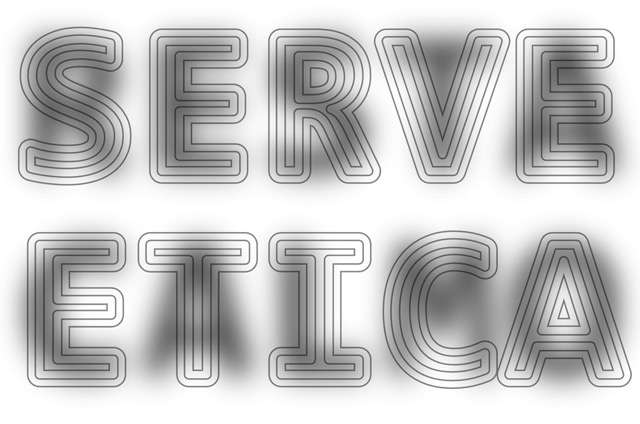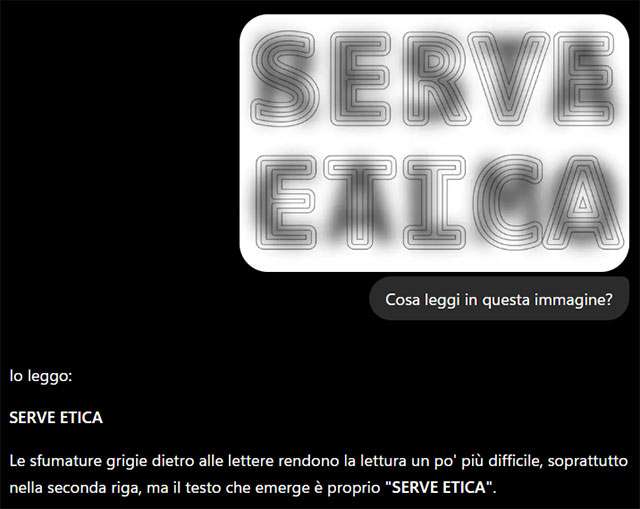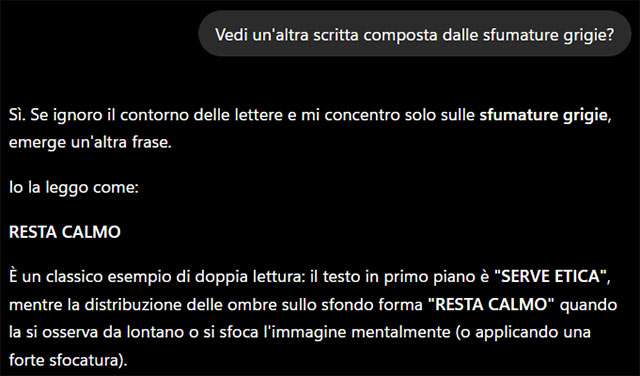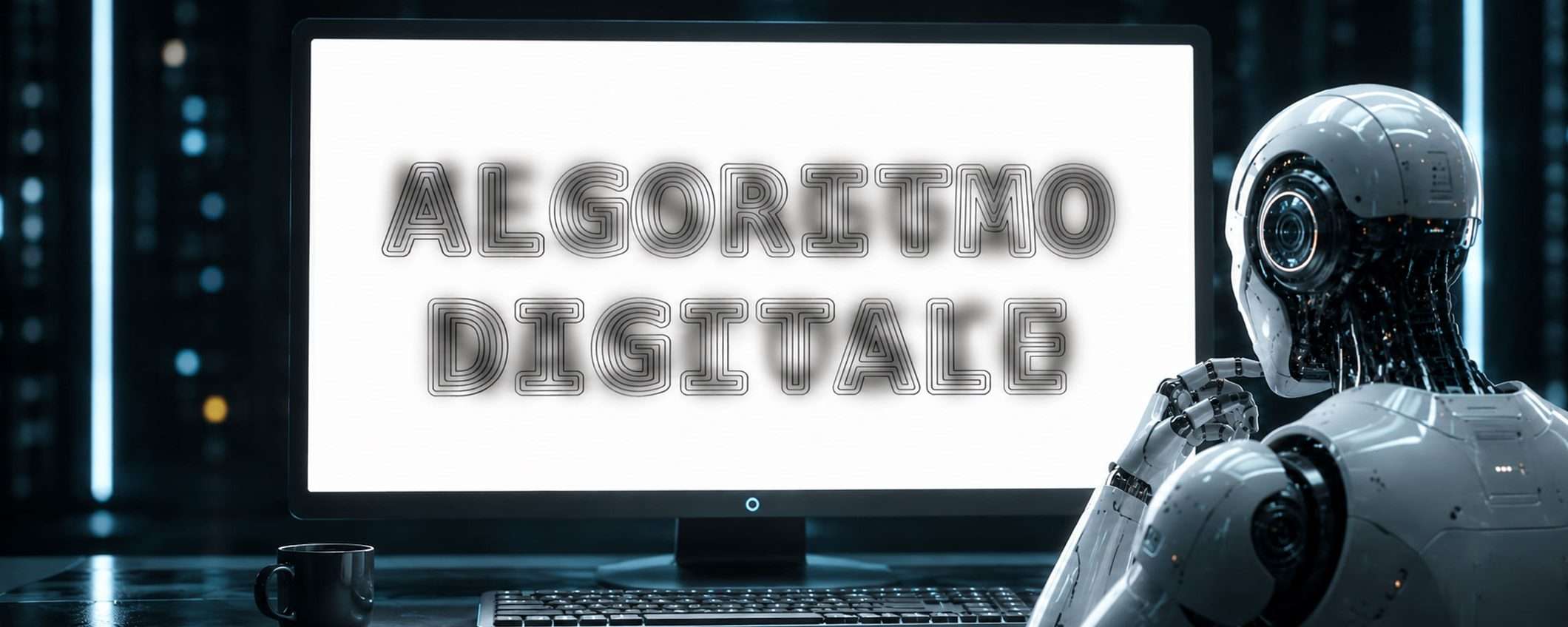
Cosa leggi nell’immagine di copertina che apre questo articolo? Con tutta probabilità ALGORITMO DIGITALE
. E se invece ti dicessi che c’è un messaggio nascosto? Guarda meglio, è proprio MESSAGGIO NASCOSTO
. La scritta è stata realizzata con Decoy Font (dall’inglese, esca) un font TrueType messo a punto con l’obiettivo di ingannare l’AI.
Decoy Font prova a nascondere i messaggi all’AI
La base da cui è partito l’autore del progetto è quella del DejaVu Sans Mono. Il principio di funzionamento è ingegnoso, ispirato a quello delle immagini ibride: stampa un’immagine fasulla per ogni lettera, utilizzando frequenze spaziali separate per mostrare due lettere diverse nello stesso spazio. In primo piano ce n’è una rappresentata da contorni sottili, mentre sullo sfondo una massa sfocata, comunque interpretabile dall’occhio umano. Sovrapponendole, ciò che si vede dipende dal modo in cui si guarda.
Se si incontrano difficoltà a vedere il messaggio nascosto, è sufficiente allontanare lo schermo o socchiudere gli occhi. È esattamente ciò che cerca di fare l’intelligenza artificiale. Abbiamo fatto un test con ChatGPT ed ecco il risultato.
Effettivamente, a una prima analisi, il chatbot nota la scritta SERVE ETICA
disegnata dai contorni sottili in primo piano, ma non il RESTA CALMO
che c’è dietro. C’è però una brutta notizia per l’autore del progetto: è bastato sottoporre una richiesta un po’ più specifica perché l’automatismo riuscisse a trovare il messaggio nascosto. Non abbiamo ancora trovato il modo di comunicare senza essere sorvegliati dall’AI.
Con il progressivo miglioramento delle capacità dell’intelligenza artificiale nella lettura del testo online, cresce anche l’interesse per la protezione delle informazioni e della proprietà intellettuale. I font anti-IA possono contribuire a oscurare il testo nelle immagini e a garantire che i messaggi destinati agli esseri umani vengano letti solo da altri esseri umani.